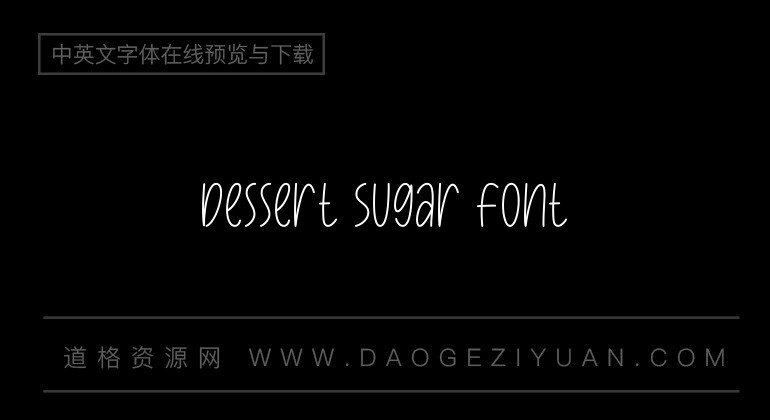
Dessert Sugar Font 是一款漂亮的手写字体,其特点是甜美而富有个性化的风格。这款字体的设计灵感源自甜点和糖果,因此它的字体线条柔和、圆润,非常适合用来设计那些甜美的、女性化的主题。它的字母形状有点类似于手写体,但却比一般的手写体更加规整和可读性更高。Dessert Sugar Font 支持英文、数字和标点符号,可以用来设计海报、印刷品、网站和社交媒体内容等等。内容介绍
Dessert Sugar Font是一款非常不错的手写艺术字体,具有很好的视觉感,适合于文化类的宣传设计、商业类品牌的广告和产品包装设计以及个性化文字排版等较多场景。